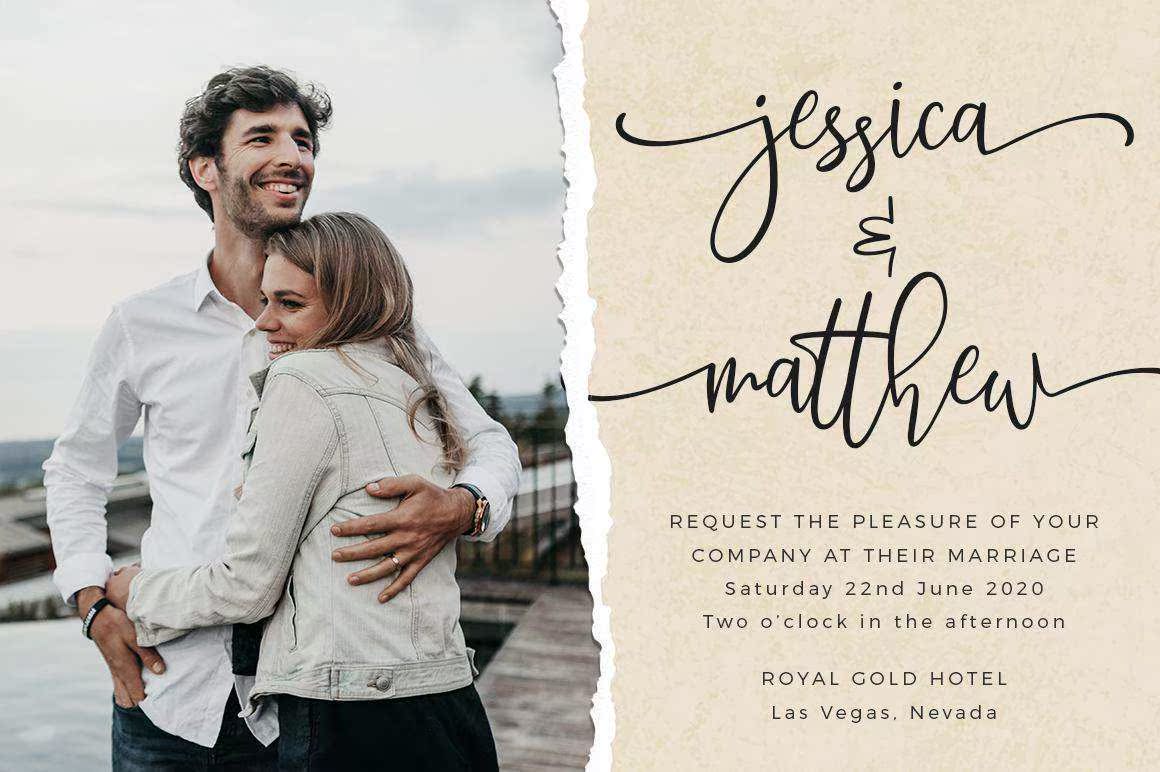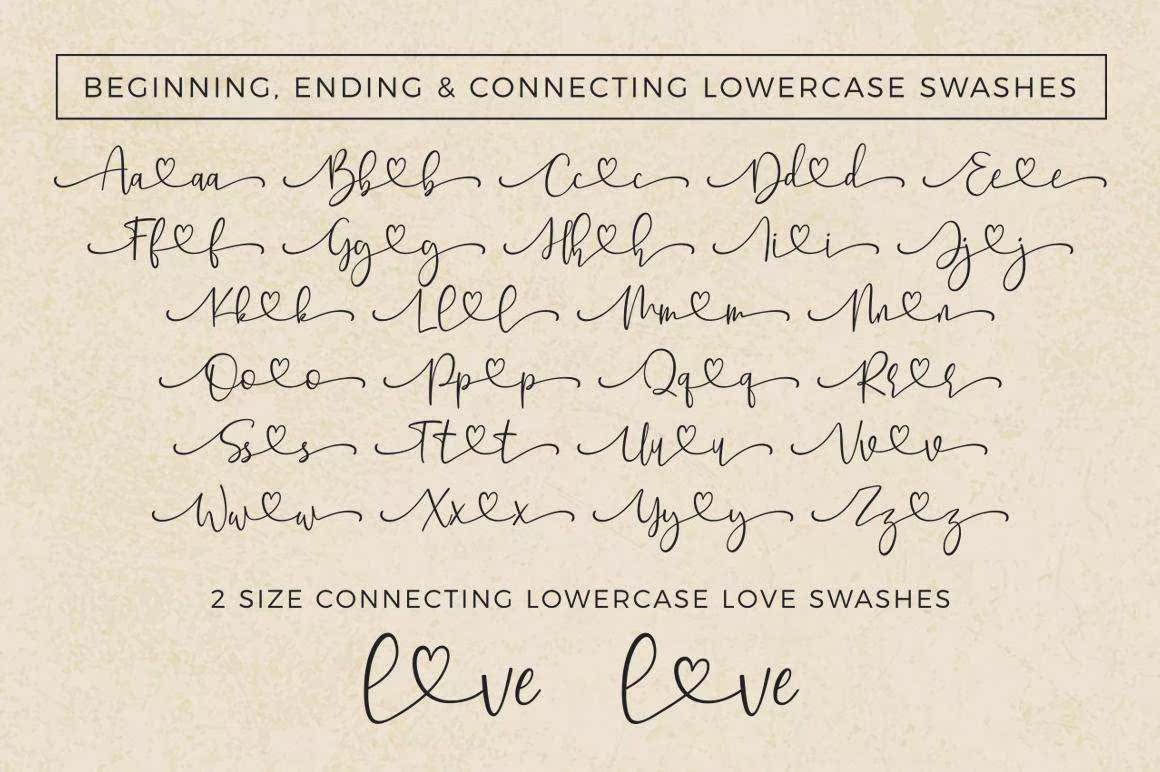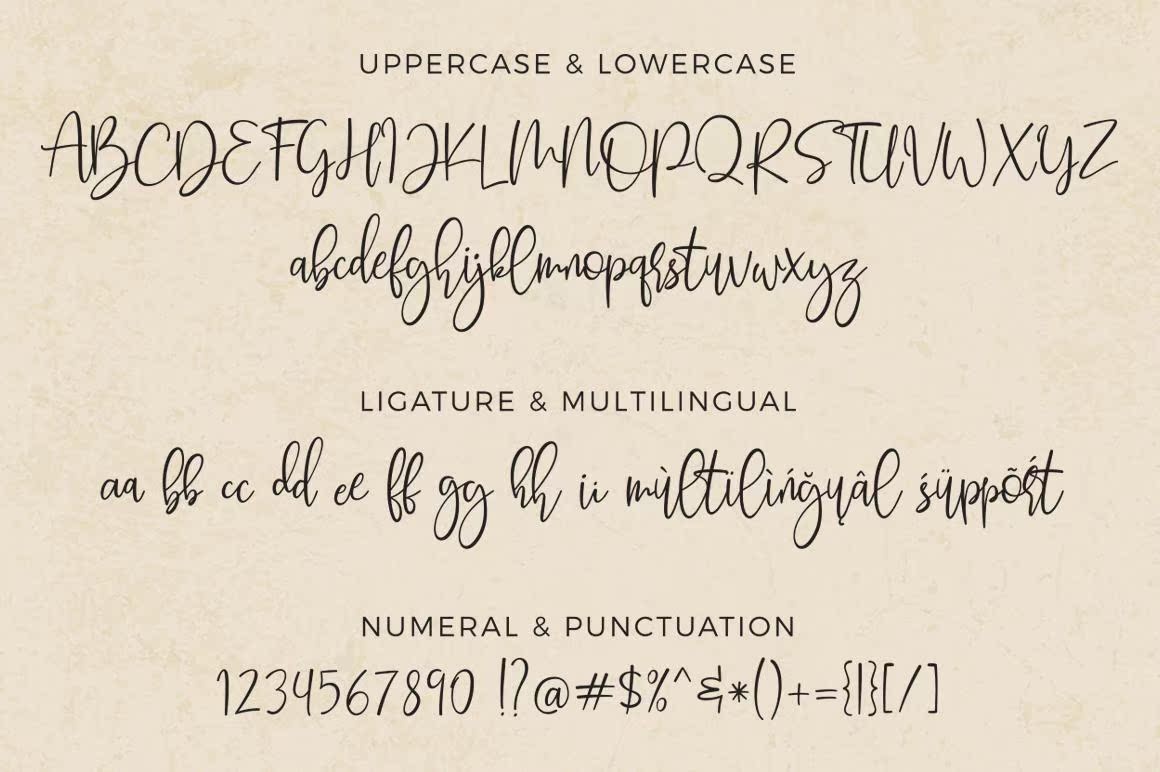
Butterjelly是一款具有手写、复杂流程的现代拼图。它充满了心形和字形。具有夸张的行程和弹性基线,Butterjelly具有不可阻挡的伤害;完美的徽标、婚礼统计、卡片、礼物设计、摄影、水印、产品包装和手写报价。Butterjelly是一款具有手写、复杂流程的现代拼图。它充满了听觉和字形。具有夸张的行程和弹性基线,Butterjelly无可阻挡的伤害;完美适用于徽标、婚礼统计、贺卡、礼品设计、摄影、水印、产品包装和手写报价。